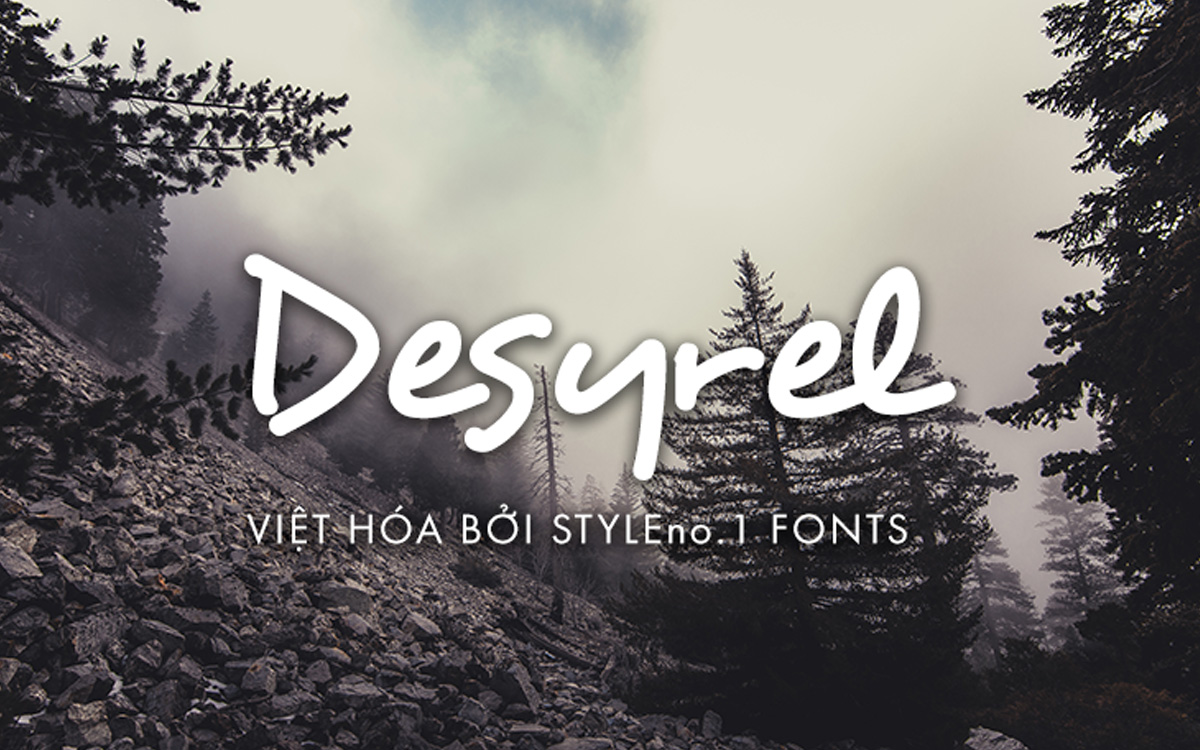
Nếu bạn đang tìm kiếm một phông chữ mang lại cảm giác ngộ nghĩnh, gần gũi và đầy sức sống cho các dự án sáng tạo của mình, font chữ SVN-Desyrel chính là sự lựa chọn hoàn hảo không thể bỏ qua. Với đường nét viết tay tự nhiên, phóng khoáng cùng nét tính cách tươi vui, font chữ này dễ dàng chiếm trọn cảm tình của người xem ngay từ ánh nhìn đầu tiên. Bộ phông chữ này đặc biệt sinh ra để dành cho các thương hiệu hướng tới đối tượng trẻ em, các dịch vụ ẩm thực cute và những sản phẩm truyền thông đòi hỏi sự ngọt ngào, đáng yêu.
Font Chữ Vui Vẻ, Dễ Thương, Hoạt Hình Cho Lĩnh Vực Trẻ Em, Đồ Ăn Cute: Khám Phá Vẻ Đẹp SVN-Desyrel
Trong thế giới thiết kế đồ họa đa dạng ngày nay, việc lựa chọn typography đóng vai trò quyết định đến 70% cảm xúc của bộ nhận diện thương hiệu. Phông chữ SVN-Desyrel nổi lên như một làn gió mới tràn đầy năng lượng tích cực, kết hợp hoàn hảo giữa nét vẽ tay thủ công linh hoạt và phong cách hoạt hình (cartoon) sống động. Đây là công cụ đắc lực giúp các nhà thiết kế biến những ý tưởng đơn điệu trở nên sinh động, bắt mắt và ngập tràn niềm vui.
Dưới đây là chi tiết các đặc tính nổi bật và ứng dụng thực tế vượt trội của bộ font chữ SVN-Desyrel trong các dự án thiết kế chuyên nghiệp:
1. Phong Cách Nét Chữ Hand-Drawn Mềm Mại, Vui Tươi Và Đầy Cảm Xúc
SVN-Desyrel sở hữu cấu trúc nét chữ kiểu tay vẩy (script hand-drawn) mỏng nhẹ nhưng lại vô cùng thanh thoát. Khác với các dòng phông chữ nghiêm túc hay cứng nhắc, từng đường cong của SVN-Desyrel mang đến cảm giác tự do, bay bổng và đầy ngẫu hứng. Chính sự không hoàn hảo một cách cố ý trong từng nét di chuyển của con chữ lại tạo nên tính chân thực và sự ấm áp kỳ lạ.
- Đường nét uyển chuyển: Nét bút mô phỏng hoàn hảo nét viết mực nước hoặc bút dạ, mang lại hiệu ứng thị giác chân thực.
- Nhịp điệu biến hóa: Khoảng cách và độ nghiêng của các chữ cái được sắp xếp khéo léo, tạo nên một giai điệu thị giác vui tươi khi ghép thành từ và câu complete.
- Truyền cảm xúc tích cực: Giúp sản phẩm thiết kế bớt đi sự khô khan, thay vào đó là sự thân thiện, gần gũi và dễ tiếp cận với khách hàng.
2. Giải Pháp Thiết Kế Hoàn Hảo Cho Lĩnh Vực Trẻ Em Và Giáo Dục Sáng Tạo
Trẻ em là đối tượng tiếp nhận thị giác thông qua màu sắc rực rỡ và những hình khối ngộ nghĩnh. Font chữ SVN-Desyrel với phong cách hoạt hình đáng yêu hoàn toàn đáp ứng được tâm lý học thị giác của độ tuổi mầm non và thiếu nhi. Nét chữ mềm mại giúp tạo cảm giác an toàn, vui nhộn và kích thích trí tưởng tượng phong phú của trẻ.
Các ứng dụng tiêu biểu trong lĩnh vực trẻ em bao gồm:
- Sách truyện và ấn phẩm thiếu nhi: Sử dụng làm tiêu đề sách truyện tranh, bìa sách bài tập sáng tạo, thiệp mời sinh nhật hoặc bảng chữ cái tập tô.
- Thời trang và phụ kiện trẻ em: In ấn các khẩu hiệu đáng yêu lên áo thun, mũ, balo hay đồ chơi gỗ cho bé.
- Trang trí không gian: Thiết kế bảng hiệu trường mầm non, khu vui chơi giải trí, decal dán tường phòng ngủ cho trẻ.
3. Đánh Thức Vị Giác Trong Thiết Kế Bao Bì Đồ Ăn, Quán Trà Sữa Và Menu Cute
Không chỉ dừng lại ở lĩnh vực trẻ em, SVN-Desyrel còn là “vũ khí bí mật” của ngành F&B (Thực phẩm & Đồ uống), đặc biệt là các mô hình kinh doanh hướng tới giới trẻ và không gian đáng yêu. Tinh thần vui tươi của font chữ này gợi liên tưởng đến sự ngọt ngào của những chiếc bánh cupcake, vị thanh mát của ly trà sữa hay sự ngon lành của những món ăn vặt quen thuộc.
- Bao bì sản phẩm: Thiết kế nhãn dán (sticker), túi giấy, ly nhựa, hộp bánh kem với phong cách hình minh họa chibi kết hợp cùng chữ SVN-Desyrel vô cùng bắt mắt.
- Thực đơn (Menu) quán ăn: Tạo nên những bản menu quán trà sữa, tiệm bánh ngọt hay quán ăn vặt có phong cách gần gũi, giúp khách hàng cảm thấy thư giãn khi gọi món.
- Đồ họa quảng cáo ẩm thực: Tạo các bài đăng Facebook/Instagram rực rỡ thu hút các “tín đồ” ẩm thực bấm vào xem ngay lập tức.
4. Tương Thích Hoàn Hảo Tiếng Việt Với Bộ Ký Tự Việt Hóa Chuẩn Xác
Một trong những nỗi lo lớn nhất của các designer Việt Nam khi sử dụng các font chữ viết tay nước ngoài là lỗi font, thiếu dấu hoặc các dấu thanh bị đặt sai vị trí làm mất thẩm mỹ. Bản Việt hóa SVN-Desyrel đã giải quyết triệt để vấn đề này. Bộ dấu Tiếng Việt được thiết kế tỉ mỉ, đồng bộ hoàn toàn với nét vẽ gốc của font chữ, đảm bảo tính thẩm mỹ cao nhất.
- Đầy đủ dấu thanh: Các dấu sắc, huyền, hỏi, ngã, nặng và các ký tự đặc trưng như ă, ô, ơ, ư đều được chăm chút kỹ lưỡng.
- Tối ưu Kerning: Khoảng cách giữa các chữ cái chứa dấu được tinh chỉnh hoàn hảo, không bị đè nét hay quá xa nhau.
- Sử dụng linh hoạt trên nhiều phần mềm: Hoạt động mượt mà trên tất cả các phần mềm thiết kế hàng đầu như Adobe Photoshop, Illustrator, InDesign, Canva cũng như các ứng dụng dựng video như Premiere, CapCut.
5. Ứng Dụng Đa Năng Cho Ấn Phẩm Truyền Thông Và Mạng Xã Hội
Trong kỷ nguyên số, các nội dung truyền thông trên mạng xã hội đòi hỏi phải thu hút sự chú ý của người dùng trong 3 giây đầu tiên. SVN-Desyrel sở hữu khả năng làm nổi bật thông điệp chính một cách vô cùng tự nhiên. Font chữ này thích hợp làm tiêu đề (headline) trên các ảnh banner quảng cáo, thumbnail YouTube, hình ảnh bài đăng Instagram hay các mẫu câu quote truyền cảm hứng.